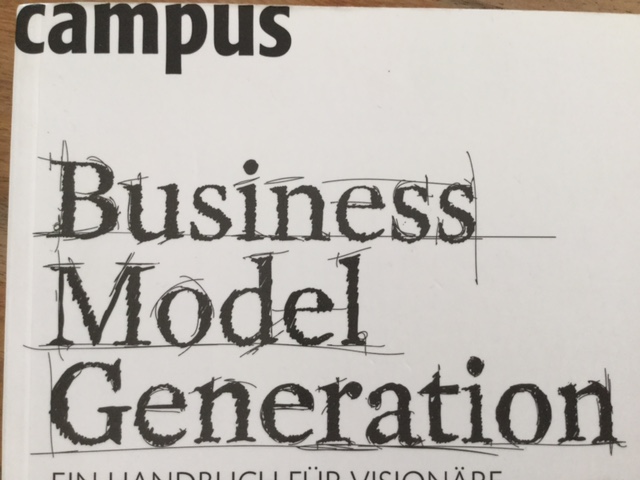
Suche Coverschrift Business Model Generation
vielleicht könnt ihr mir dabei helfen, ich suche die Titelschrift von dem Buch Business Model Generation.
Ich geh davon aus, dass diese Strichverzierungen und die Füllung händisch gemalt wurden und suche daher den originalen Font. Myfonts konnte mir dabei leider nicht weiterhelfen.
Der originale ist eine Times.
Die Times hatte ich auch schon auf dem Schirm, aber das Versal-G der Times passt leider nicht.